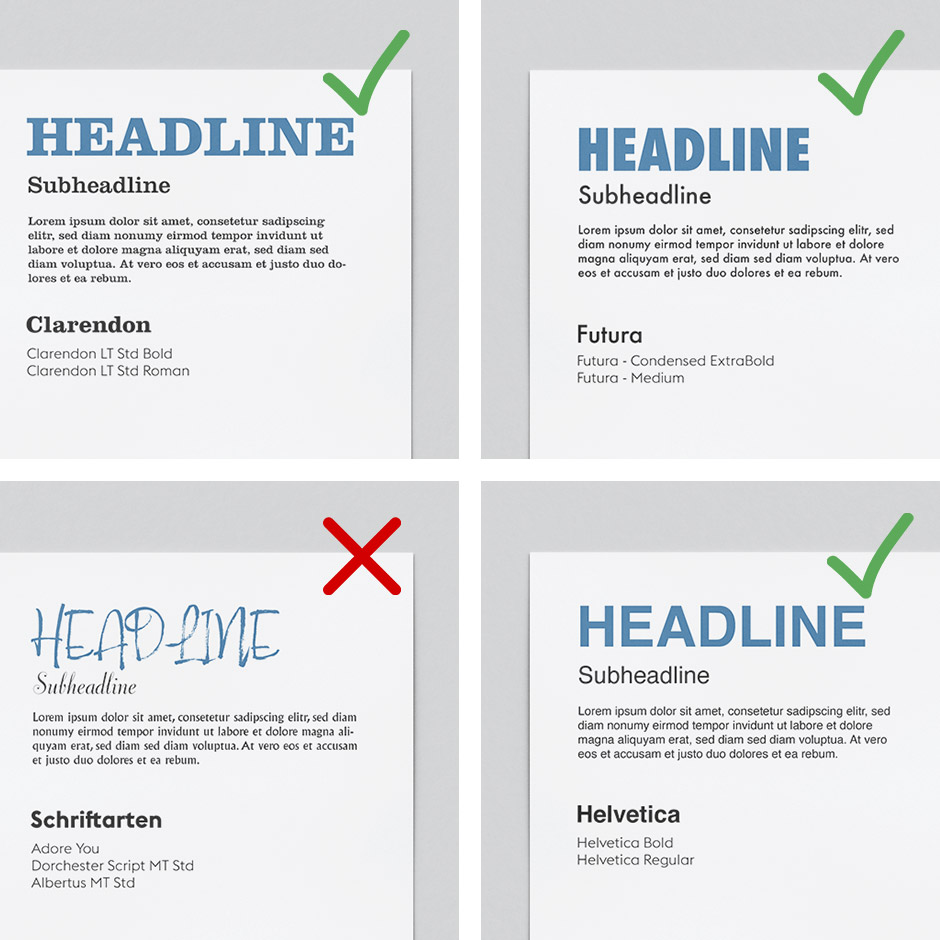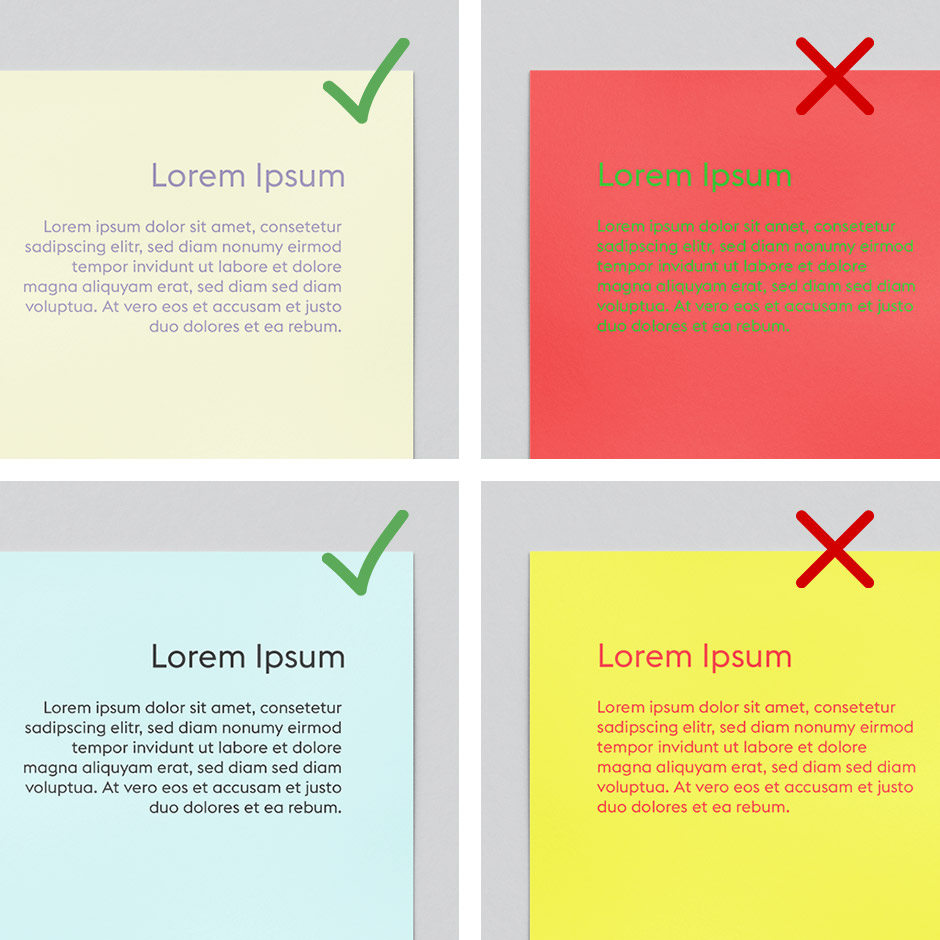
Mit Plakaten als Außenwerbung erreichen Sie eine große Zielgruppe – kein Wunder, die Reichweite in der Öffentlichkeit ist hoch. Aber wie sorgen Sie dafür, dass sich alle Blicke auf Ihre Botschaft richten und diese auch Gedächtnis bleibt? Hier gibts einige Tipps, die Sie bei Ihrem Plakatdesign beachten sollten.
An einem clever gestalteten und gut sichtbar angebrachten Plakat kommt kaum jemand vorbei, ohne die aufgedruckte Botschaft wahrzunehmen und zu lesen. Aber neben dem idealen Anbringungsort gibt es bei der Planung Ihrer Werbemaßnahme noch viele andere Faktoren zu bedenken. Das geht schon ganz zu Beginn los: Wie gestalten Sie überhaupt das Plakat so, dass Passanten möglichst gerne und lange einen Blick darauf werfen?
Bedenken Sie: Im Schnitt werden Plakate nur 3 – 5 Sekunden betrachtet. Daher müssen die wichtigsten Inhalte innerhalb weniger Sekunden scanbar sein und sofort ins Auge springen. Denn kaum jemand bleibt extra stehen, um ein Plakat zu lesen, sondern überfliegt es nur im Vorbeilaufen. Dementsprechend sollten Sie bei Ihrem Plakatdesign einige wichtige Eckpunkte beachten.
Allgemein gilt: Bei der Plakatgestaltung gibt es keine fixen Vorgaben. Hier spielen auch persönliche Präferenzen, Corporate Design Vorgaben, Ihre Zielgruppe sowie die Branche Ihres Unternehmens eine Rolle. Dennoch gibt es einige Tipps, mithilfe derer Sie ein ansprechendes optisches Ergebnis garantieren können – quasi die Basiszutaten Ihres Erfolgsrezepts.
Der Aufbau des Plakats
Zuallererst sollten Sie sich über den Aufbau Ihres Plakats Gedanken machen. Welche Elemente sollen auf dem Plakat zu sehen sein? Wie viel Platz sollen sie auf der Gesamtfläche des Plakats einnehmen und wo sollen sie platzieren werden? Das Ziel: Ihr Plakat soll Aufmerksamkeit erregen, Interesse wecken und eine klare Botschaft vermitteln. Der Betrachter sollte sich in wenigen Sekunden erschließen können, was die Aussage Ihres Plakats ist und die wichtigsten Informationen herausfiltern können.
Daher sollten Sie als Grundlage für Ihr Plakatdesign zuerst einmal den Aufbau skizzieren. So fällt gegebenenfalls auch schnell auf, ob bestimmte Elemente herausgekürzt werden müssen, weil das Plakat ansonsten zu überladen wirkt oder ob an einigen Stellen noch Lücken im Design auftauchen, die Sie mit Schrift oder Bildelementen füllen.
Typische Elemente für die Plakatgestaltung sind:
- Headline
- Subline
- Bildelemente
- optional: weitere knappe Textelemente (z.B. Preis, Datum)
- Ihr Logo
Headline, Subline und weiterer Text:
Wenn es um Text auf Plakaten geht, so gilt der Grundsatz: so wenig wie möglich, so viel wie nötig. Behalten Sie im Hinterkopf, dass Passanten Ihr Plakat im Schnitt nur wenige Sekunden im Vorbeigehen betrachten. Wählen Sie daher als Headline eine klare, interessante Überschrift von maximal 5 Worten, die bestenfalls in eine Zeile passt. Die Headline sollte etwa 15 % der Formathöhe des Plakats entsprechen. Zusätzlich zu Ihrer Kernbotschaft können Sie auch eine ergänzende Subline in ca. 7 – 10 % der Formathöhe hinzufügen.
Falls weiterer ergänzender Text nötig ist, um Ihre Botschaft verständlich zu transportieren, sollten Sie diesen zur besseren Lesbarkeit in möglichst kleine Textbausteine unterteilen. Achten Sie auch hier darauf, die Textmenge so gering wie möglich zu halten, sodass die Inhalte möglichst schnell überflogen werden können. Beschränken Sie sich außerdem auf inhaltlich relevante Informationen. Welche das sind, hängt natürlich stark davon ab, wofür Ihr Plakat wirbt. Handelt es sich um eine Produktwerbung, so könnte der Preis für Ihre Leser interessant sein. Bewerben Sie ein Event, so sollten Sie das Datum und den Veranstaltungsort in Ihrem Plakatdesign ergänzen. In jedem Fall gilt: Bringen Sie Ihre Botschaft in wenigen Worten auf den Punkt.
Passen Sie die Textmenge der Umgebung Ihres Plakats an
Auch die zukünftige Platzierung des Plakats ist bei der Festlegung der Textmenge entscheidend. Wollen Sie es an einer Straße platzieren, um die Aufmerksamkeit vorbeifahrender Autofahrer zu erregen, sollten Sie nur wenige, großformatige Worte wählen. Denn da die Aufmerksamkeit Ihrer Zielgruppe hier hauptsächlich dem Straßenverkehr gilt, ist nur ein kurzer Blick auf Ihre Botschaft möglich. Soll Ihr Plakat allerdings an der Werbewand einer Bushaltestelle hängen, darf es ruhig etwas mehr Text sein: Denn hier haben Sie es mit einer Zielgruppe zu tun, die, um die Wartezeit auf das Verkehrsmittel zu verkürzen, bestimmt auch gerne einen genaueren Blick auf die Plakatinhalte wirft.
Bildelemente:
Bilder bleiben im Kopf. Machen Sie sich das zunutze, indem Sie bei der Plakatgestaltung grafische Elemente gezielt als Blickfang einsetzen. Und das gerne großflächig: Bildelemente dürfen auf Ihrem Plakat ruhig den meisten Platz einnehmen und großflächig prominent platziert werden. Bei Bildmotiven und Produktbildern ist eine Größe von etwa 40 – 50 % der Formathöhe des Plakats angemessen.
Allgemein gilt: Wählen Sie für Ihr Plakatdesign Bildmotive, die einen positiven Eindruck hinterlassen. Natürlich sollten Sie bei der Wahl der Bildelemente auch auf das Gesamtbild und ein harmonisches Zusammenspiel mit den Textelementen Ihres Plakates achten. Gibt es auf Ihrem Plakat ohnehin schon viel zu lesen, so sollten Sie ein dezentes Bildmotiv wählen, um die Aufmerksamkeit nicht vom schriftlichen Teil wegzulenken. Dient das Bildmotiv als Eyecatcher, so darf es ruhig etwas ausgefallener sein. Lassen Sie außerdem genug Abstand zwischen Text und Bild oder dunkeln Sie bestimmte Bildbereiche zur besseren Lesbarkeit ab oder heben Sie sie farblich hervor.
Einige positive Beispiele für eine stimmige Farbkombination sehen Sie hier:
Fazit: mit cleverem Plakatdesign zum Erfolg
Plakate zeigen Wirkung – nicht umsonst sind sie seit jeher der absolute Klassiker der Außenwerbung mit langer Erfolgsgeschichte. Genau deshalb sollten Aufbau, textlicher Inhalt sowie grafische Gestaltung gut überlegt sein: Denn das ist der Schlüssel zum Erfolg Ihrer Werbemaßnahme. Wenn Sie Ihr Plakat nun noch clever platzieren und geeignetes Plakatpapier wählen, steht einer erfolgreichen Plakatkampagne nichts im Wege.